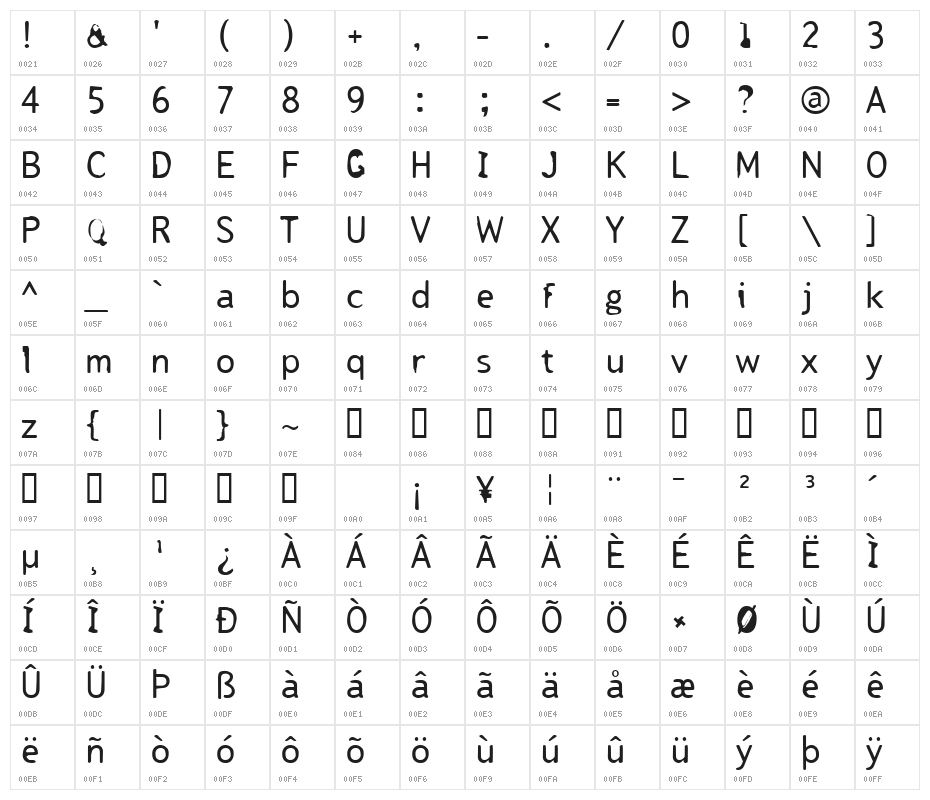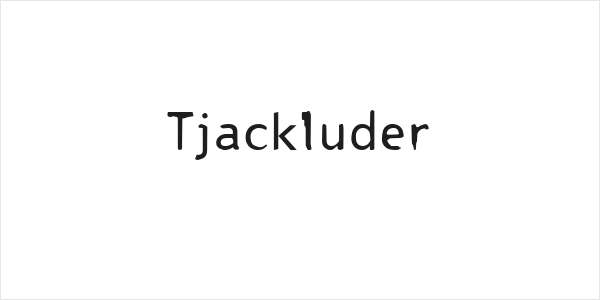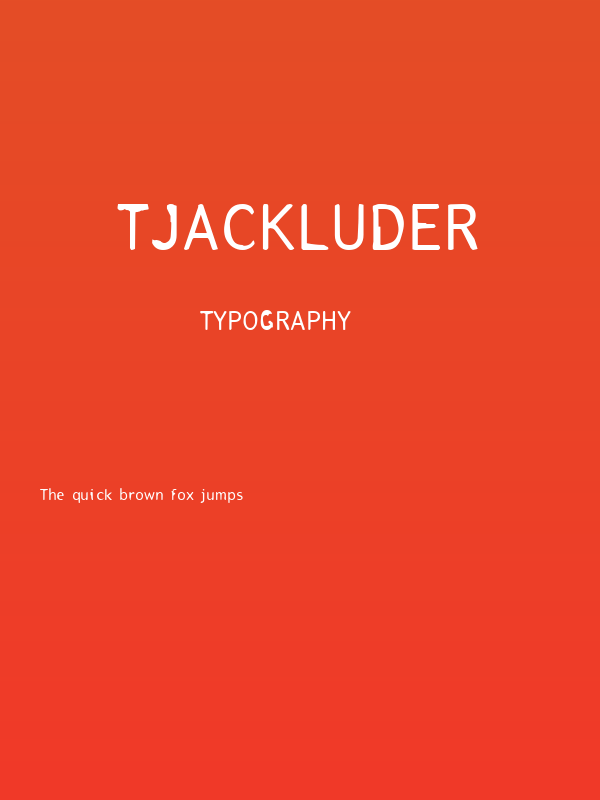
Tjackluder Font
✎ Distorted Eroded
| Vorgeschlagene Projekte | Ideal for creative projects such as children's books, artistic posters, and playful branding materials. |